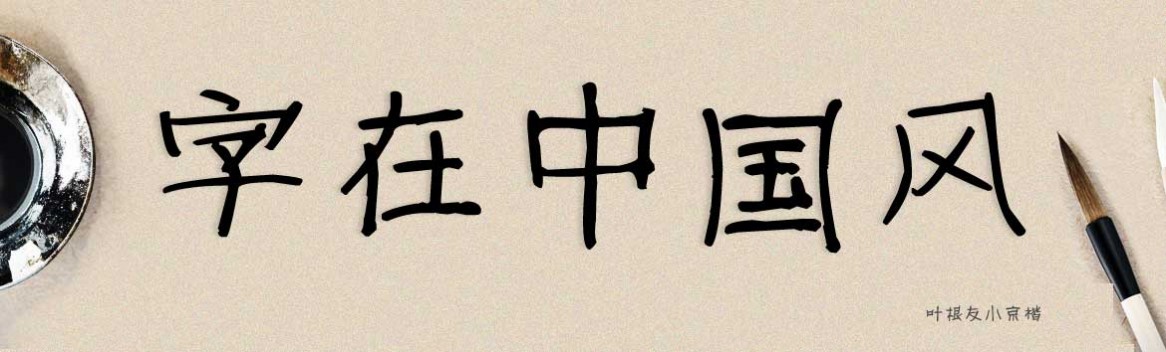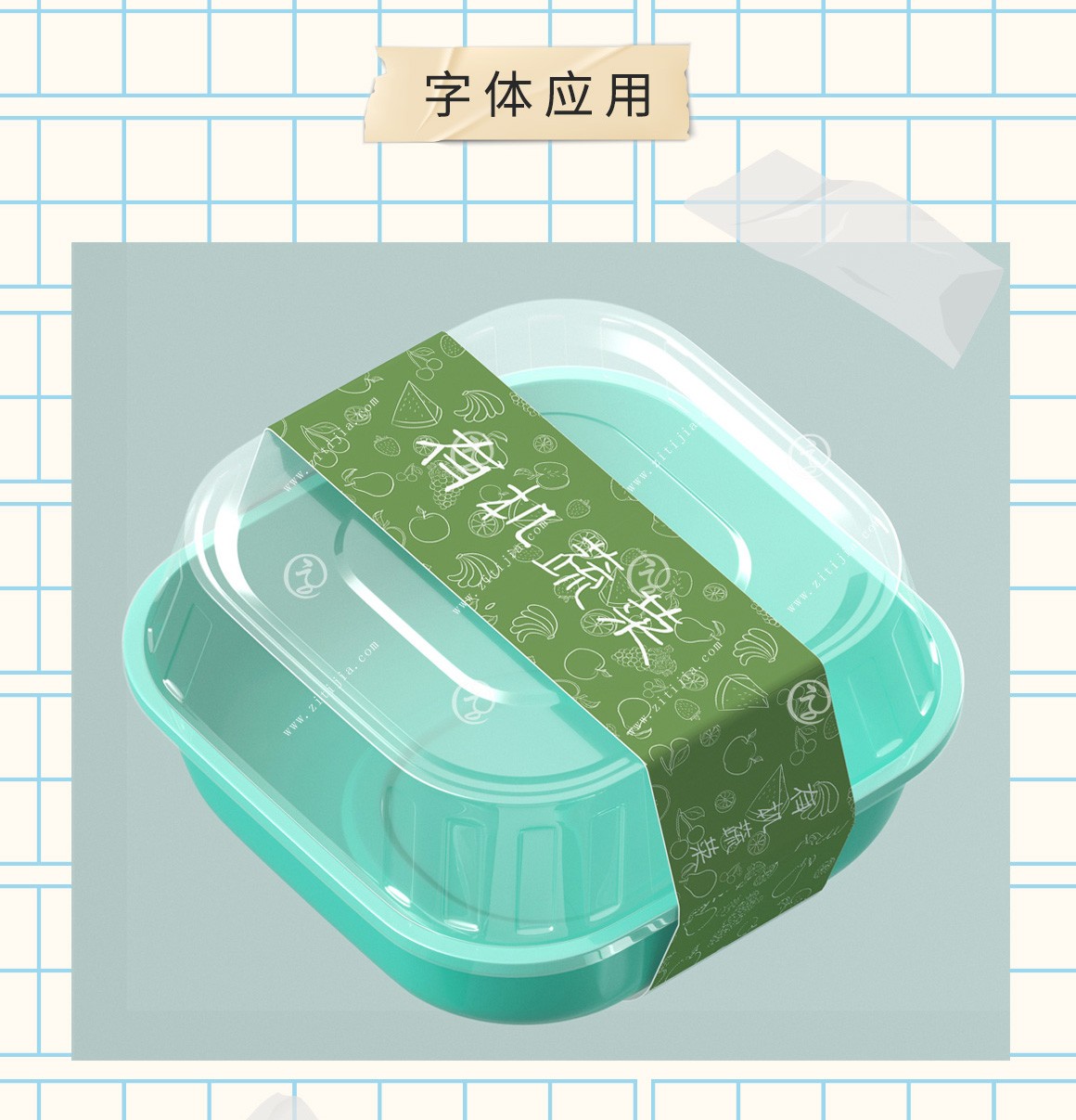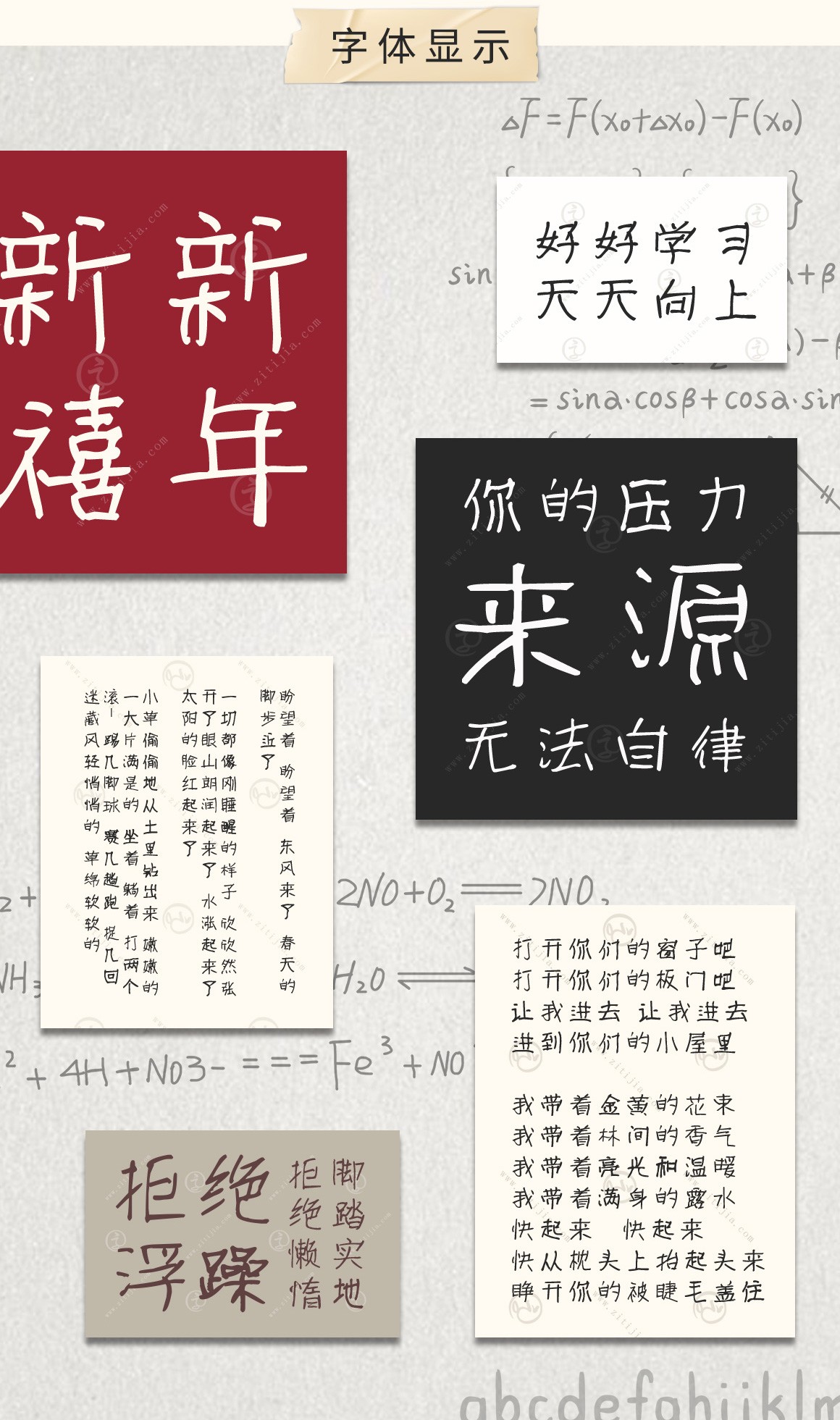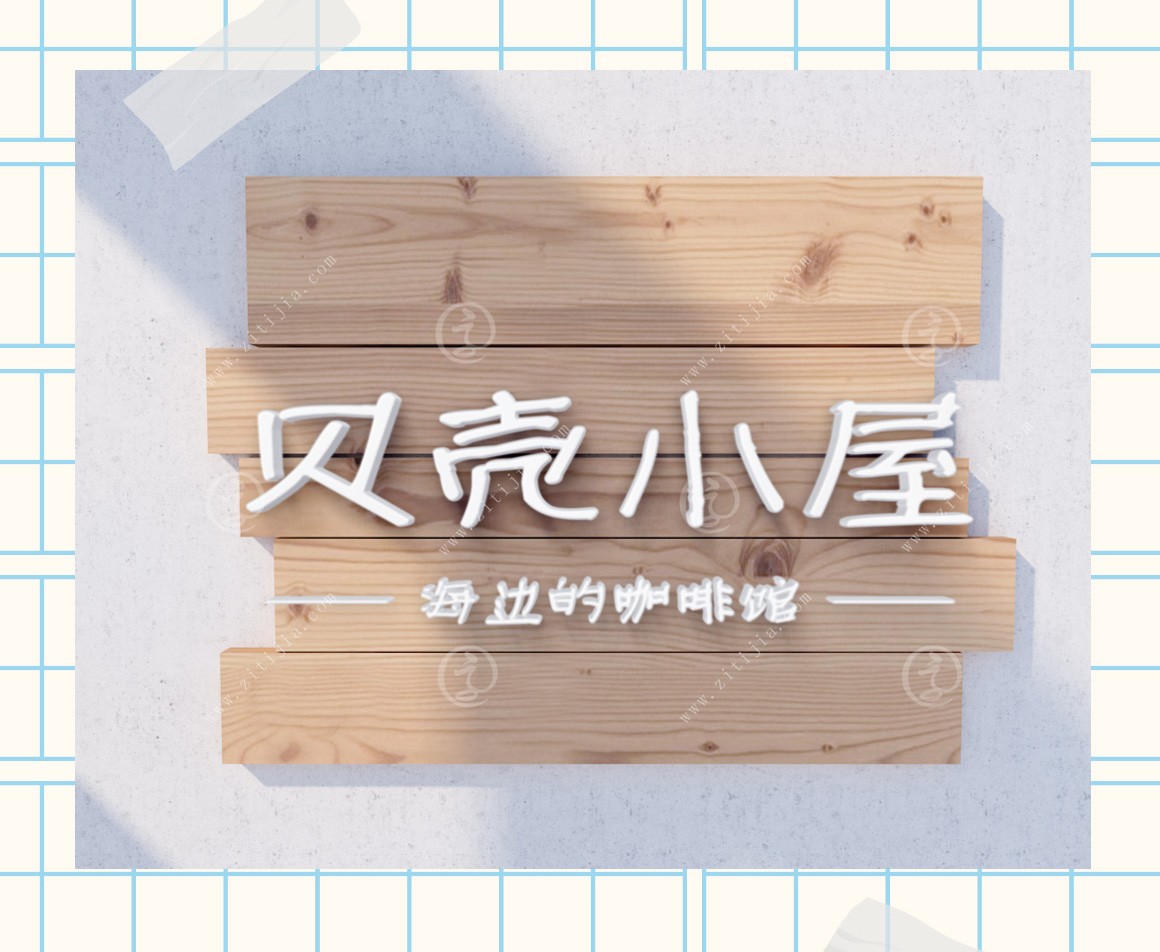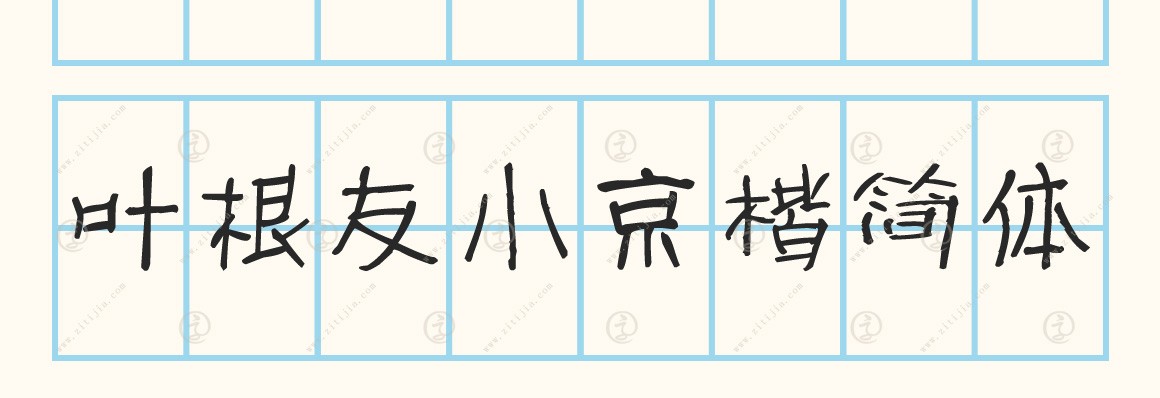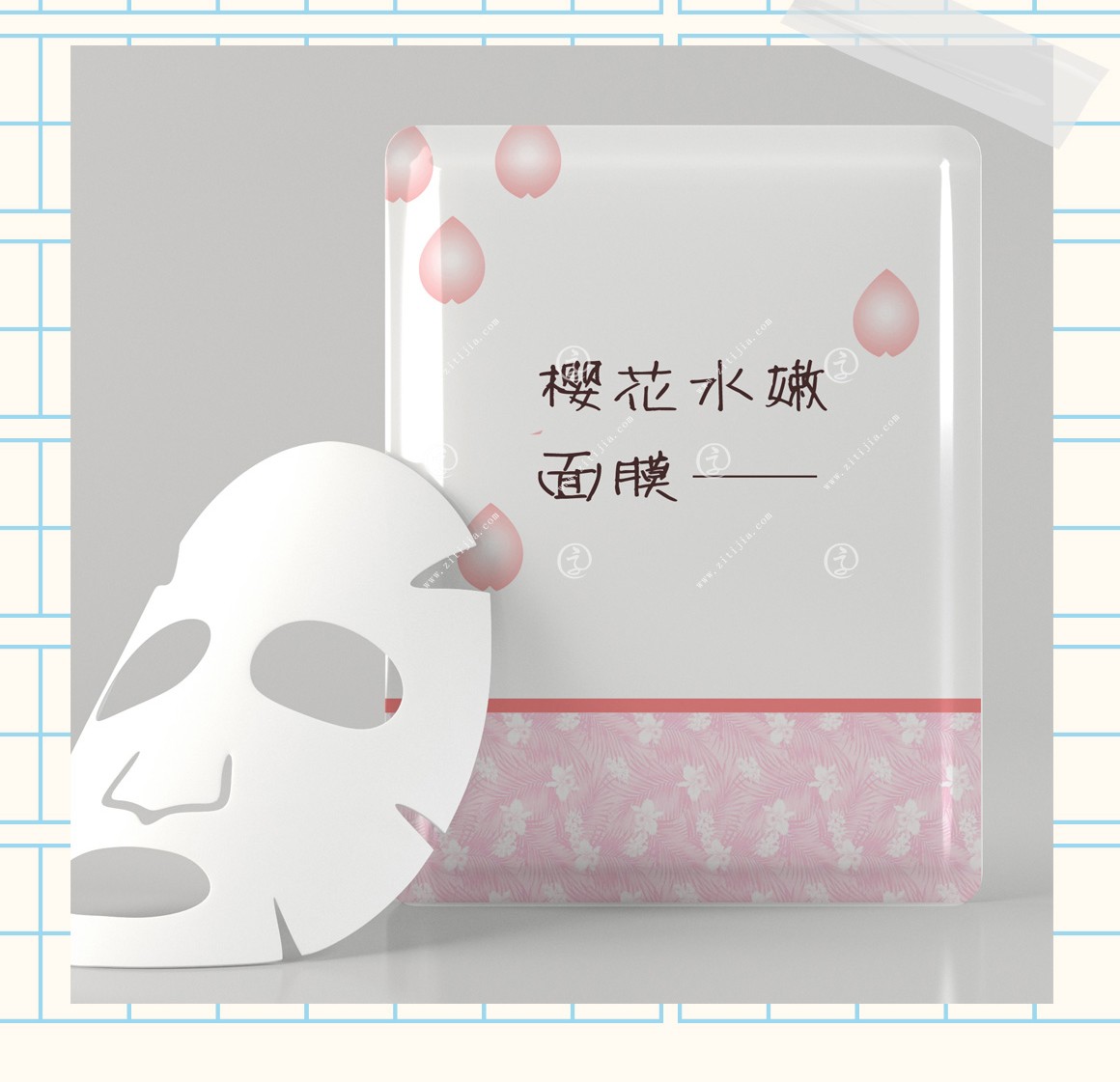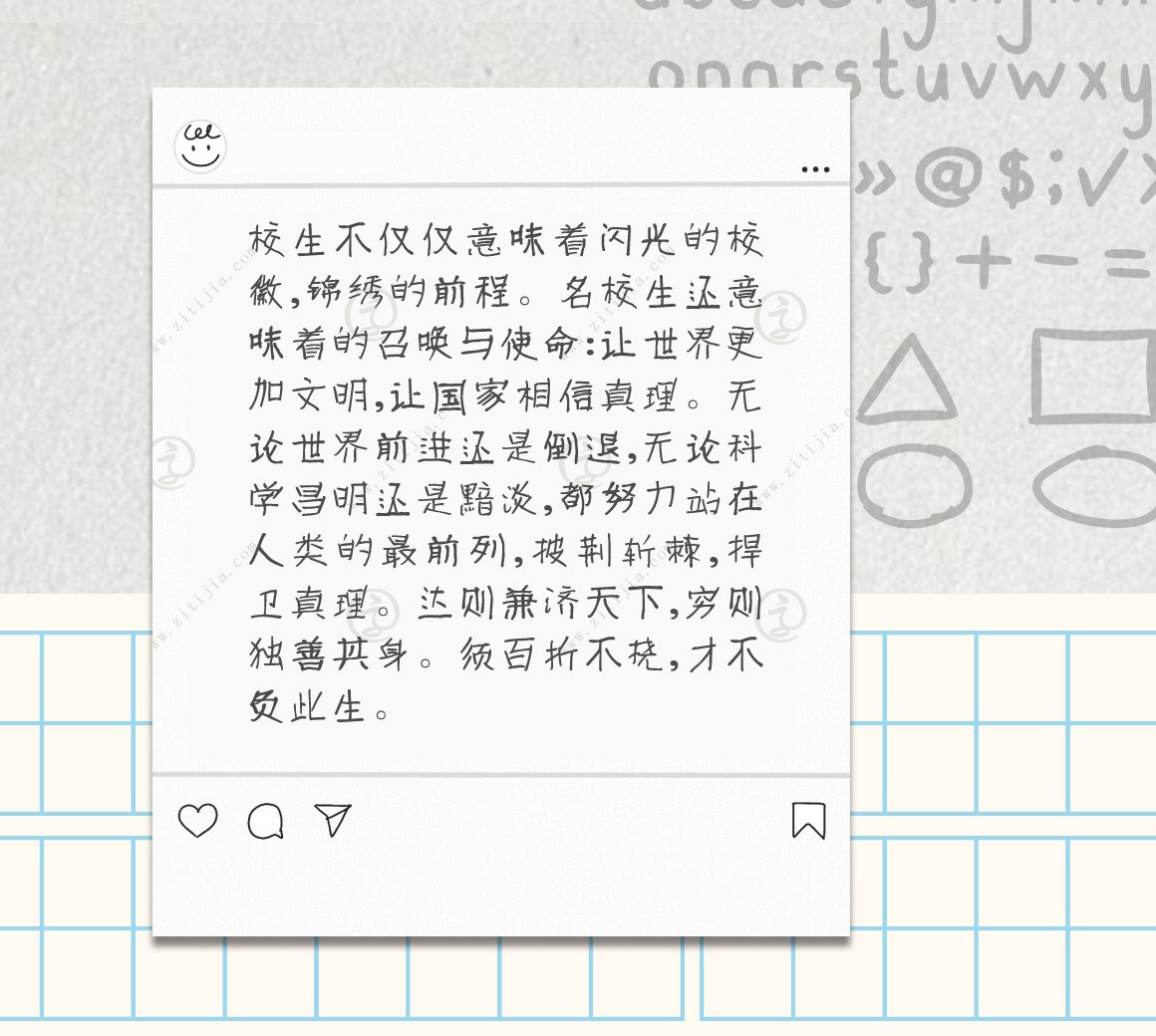
葉根友小京楷簡體
字體作者:葉根友
創(chuàng)作年代:2010年
字體字?jǐn)?shù):6763個中文漢字以及其他英文字母和阿拉伯?dāng)?shù)字
字體介紹
葉根友小京楷簡體一款類似于小學(xué)生手寫字體的手寫楷書字體,平凡中透露出一種書卷氣,流暢的風(fēng)格,內(nèi)秀的字體,如果用于中國手寫風(fēng)的載體設(shè)計會有更好的效果。